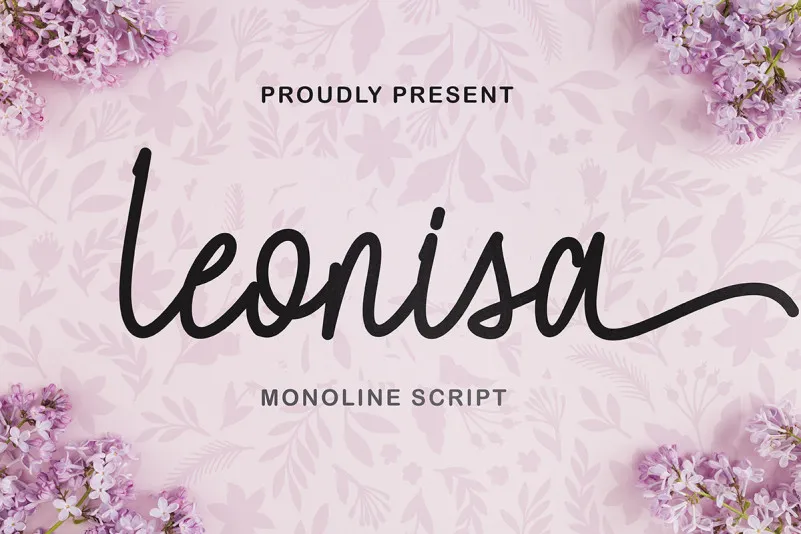
Leonisa Font – Download Grátis
A Leonisa Font é mais do que uma simples escolha tipográfica; ela é a elegância em cada letra, o respeito por cada detalhe e o amor pelo bom design. Confeccionada com grande cuidado pela designer Yoga Letter, essa fonte é um testemunho de qualidade e sofisticação. Instalar ou usar esta fonte é não apenas adquirir uma herramienta gráfica versátil, mas também aceitar as diretrizes da nossa convenção de uso do produto. É um compromisso entre criatividade e responsabilidade que valoriza a beleza do texto e o bom gosto na composição visual. Instale ou use a Leonisa Font para explorar novos horizontes em seu design editorial, gráfico ou tipográfico. Não importa qual seja sua necessidade de criação, ela tem o poder de torná-la única e impecável, fazendo da sua marca uma verdadeira obra-prima no mundo digital.